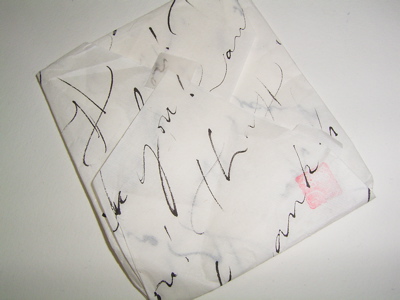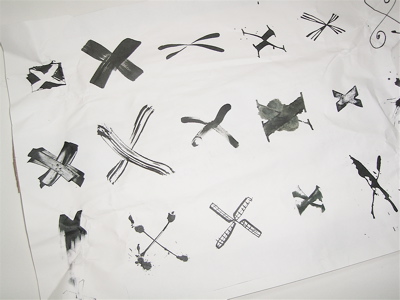
つつみがみ
ブリュージュからB氏よりものが送られて来ました。
ぐるぐる卷きだったので、カッターで切って荷物を開けました。
ぎゃぎゃ〜!
中からこんなに素敵な「X」が出て来たのです。(それなのにはじっこ切ってしまった〜)
ひとつひとつが、もう・・なんて面白い!何で書いたのかな〜と思えるものばかりです。指で書いたみたいなのもありますね。ニジニジのも、良い味わいです。
ふつうなら、あ、失敗と思うものでも、こうして集めると非常によい感じ。
これは手書きではなく印刷ですが、一体何に使ったものかしらん?
いろいろな人が書いたのか、同じ人が作ったのか、それも不明ですが、ひとつの文字をこうして突き詰めて行くのは、絶対に面白い。終わりがないかもしれませんね。
半紙にただ、thank youと書いてあるだけですが、心がこもっているのが本当によくわかります。だから、いつまでも捨てられません。
だから、練習に失敗した紙だって、そのままラッピングペ―パーになりますよね。
みなさま、くちゃくちゃぽい、せずに、取っておきませう。